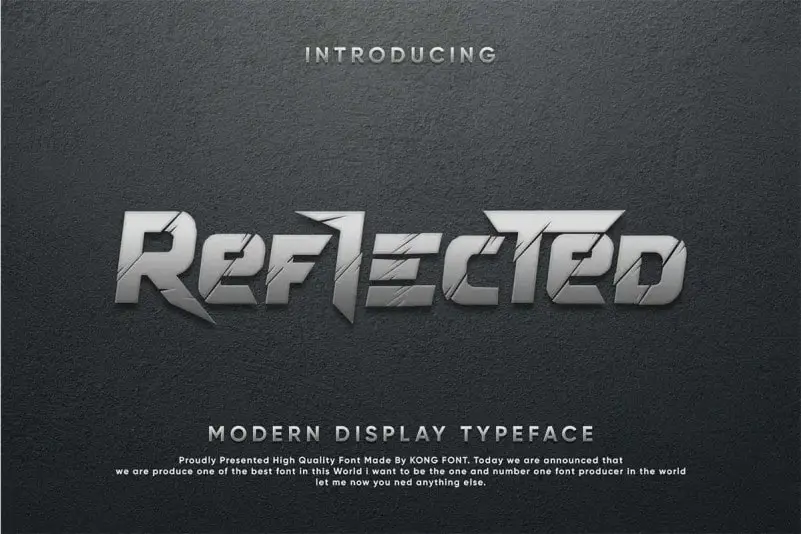
A Reflected Display Font foi criada para atender à necessidade de letras pesadas ou grossas. Ela é uma criação do famoso designer de fontes, fontkong, disponível na plataforma 99designs. Esta font destaca-se por oferecer tanto um tipo regular quanto um bold italic, com suporte a números e símbolos. É muito adequada para vários meios, incluindo capas de livros, revistas, jornais, banners publicitários em cafeterias, listagens de menu em restaurantes, páginas web, suas marcas ou até mesmo como um logotipo. A fonte reflete a sua versatilidade e permite que você exiba seu design com um toque distintivo nas mídias digitais e impressas. Não perca essa oportunidade para enriquecer o aspecto visual de seus projetos, seja ele físico ou digital.